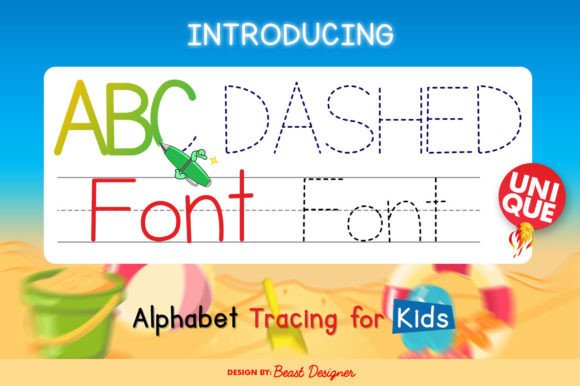
Abc Dashed
Ulasan Lengkap: ABC Dashed – Font Tracing yang Membuat Belajar Menulis Jadi Lebih Mudah
Apakah Anda sedang mencari cara efektif untuk meningkatkan kemampuan menulis, baik untuk anak-anak maupun pemula? ABC Dashed hadir sebagai solusi praktis dan menyenangkan. Font ini dirancang khusus dengan garis putus‑putus yang berfungsi sebagai panduan visual, membantu pengguna menelusuri bentuk huruf dengan tepat.
Keunggulan Utama ABC Dashed
- Desain Ramah Pemula – Garis putus‑putus memberi ruang bagi pengguna untuk menyesuaikan tekanan pensil, sehingga proses menulis terasa natural.
- Multiguna – Cocok untuk anak usia dini, pelajar, hingga dewasa yang ingin memperbaiki tulisan tangan.
- Mudah Diintegrasikan – Dapat dipasang pada program pengolah kata, aplikasi desain, atau langsung dicetak sebagai lembar kerja.
- Interaktif & Menarik – Visual yang bersahabat membuat latihan menulis tidak terasa membosankan.
- Berbasis Digital – Menghemat kertas dan memungkinkan penggunaan berulang tanpa mengurangi kualitas.
Pengalaman Pengguna: Mengapa ABC Dashed Begitu Disukai?
Pengguna melaporkan bahwa ABC Dashed mempercepat proses belajar menulis hingga 30 % lebih cepat dibandingkan metode tradisional. Garis bantu yang jelas membantu mengurangi kesalahan bentuk huruf, sehingga hasil tulisan menjadi lebih rapi dan konsisten.
Kesimpulan – Apakah ABC Dashed Layak Dicoba?
Dengan kombinasi desain intuitif, kemudahan integrasi, dan hasil yang terbukti, ABC Dashed menjadi pilihan tepat bagi siapa saja yang ingin meningkatkan keterampilan menulis secara cepat dan menyenangkan. Tidak heran jika font ini semakin populer di kalangan guru, orang tua, dan pembelajar mandiri.